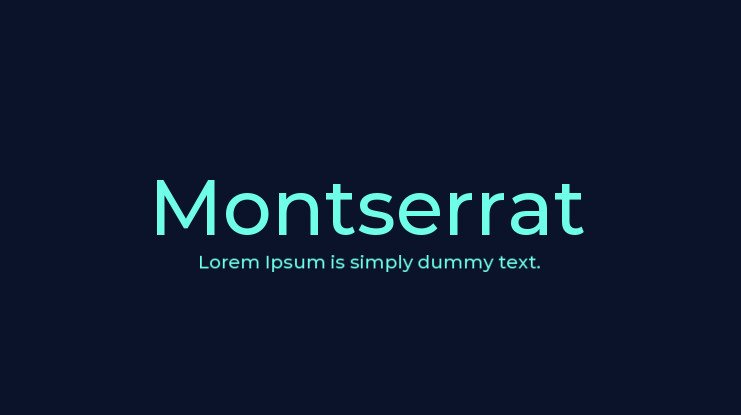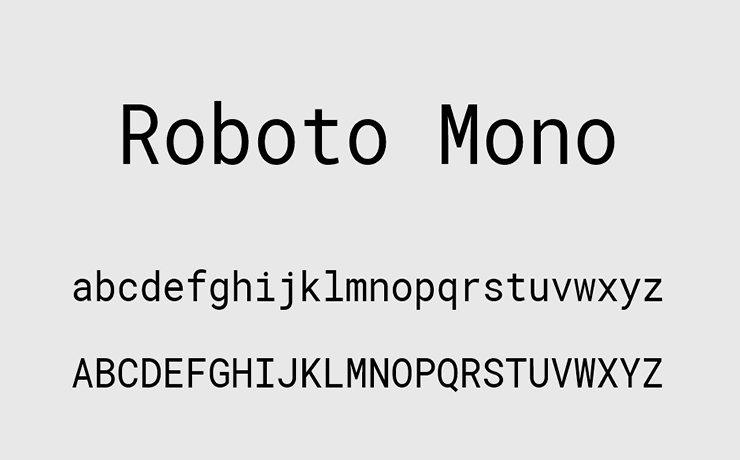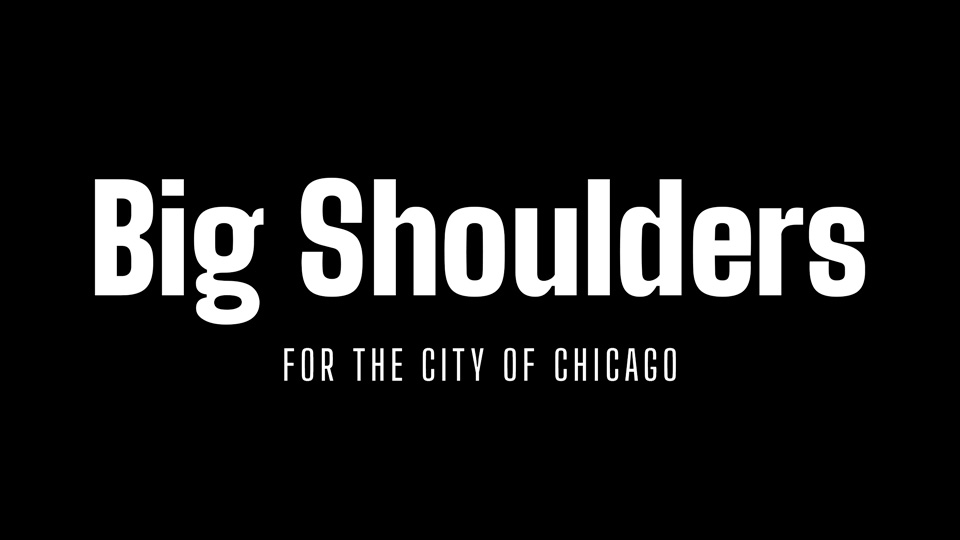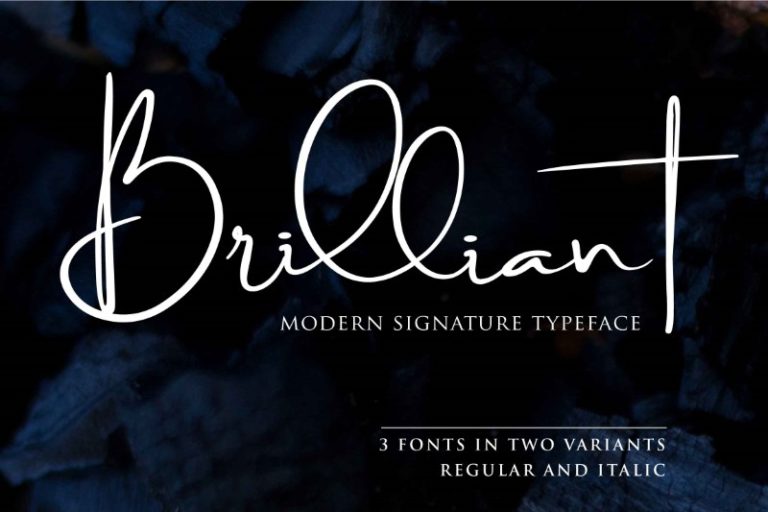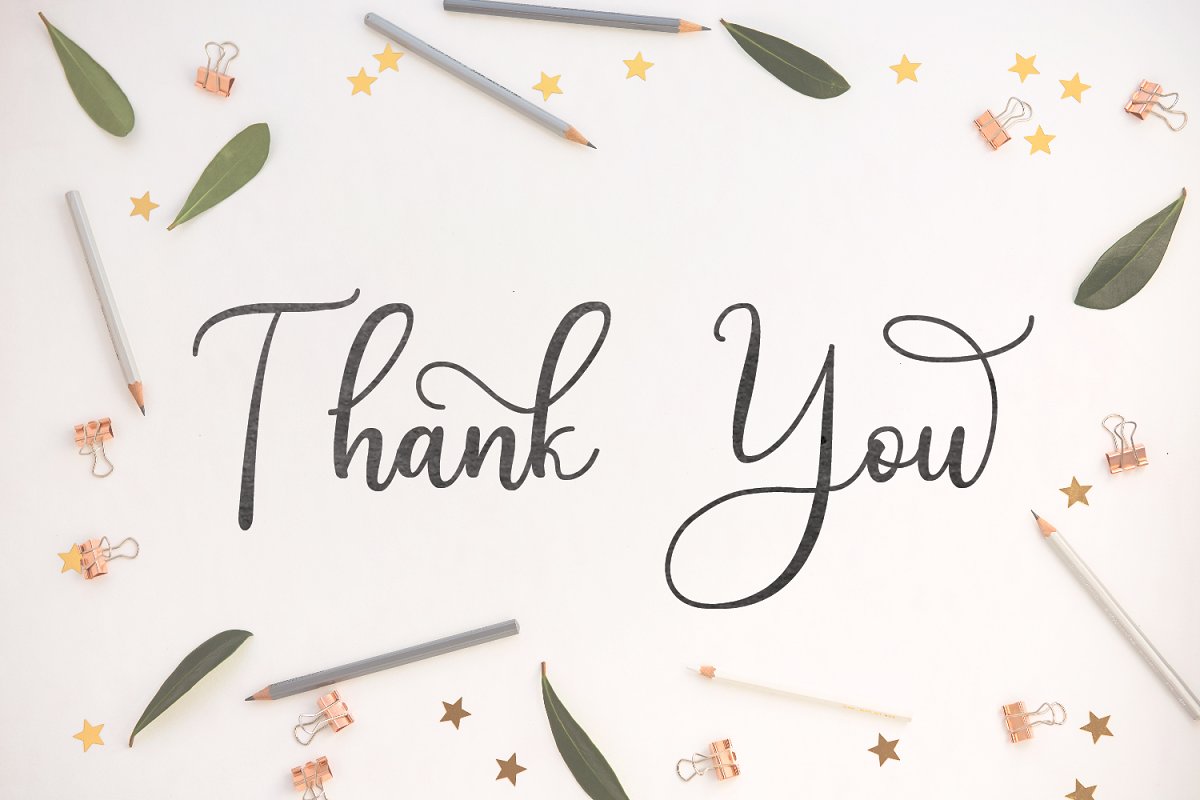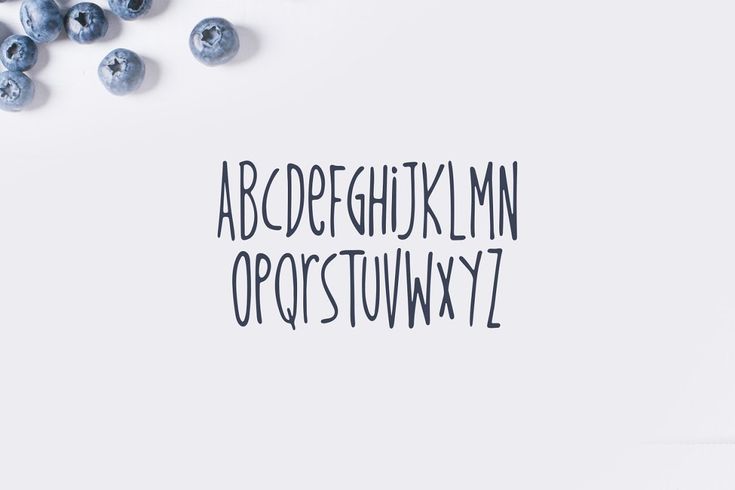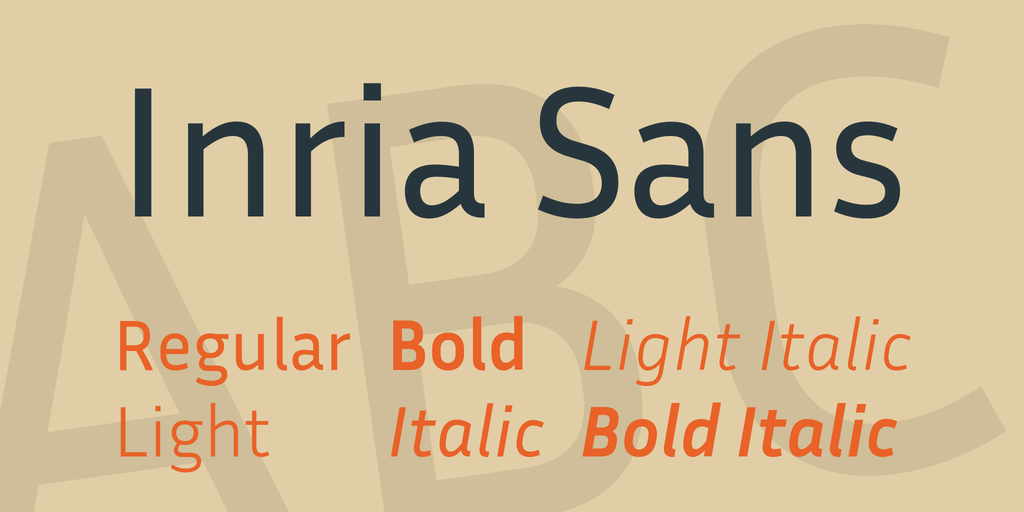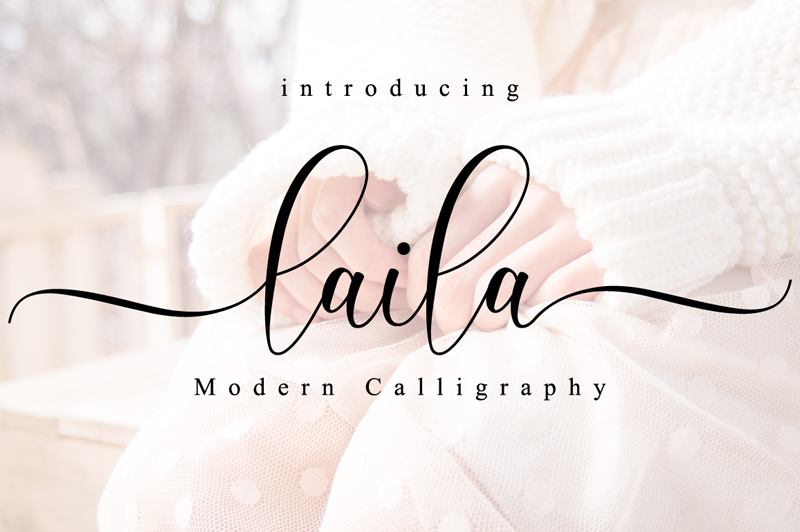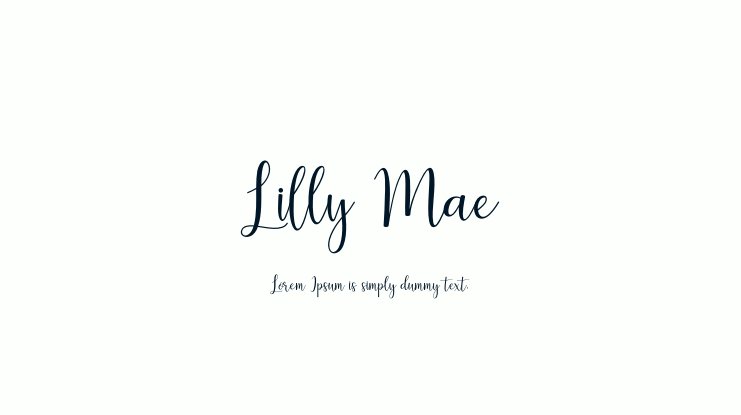
Để có một tác phẩm hoàn chỉnh, thu hút được người người xem, các designer thường sử dụng những font chữ đẹp cho thiết kế để giúp những tác phẩm trở nên sáng tạo, chuyên nghiệp hơn. Mỗi font chữ khác nhau đều biểu đạt những tính cách, thông điệp riêng biệt mà tác phẩm muốn hướng đến. Hãy cùng tìm hiểu những font chữ đẹp cho thiết kế đang được các designer ưa chuộng nhất hiện nay nhé!
Bộ sưu tập Font chữ thiết kế
Laila font
Font chữ này là kiểu kết hợp kết cấu tự nhiên với độ cứng của serif, rất thích hợp để dùng cho việc tạo thêm các điểm nhấn trên homemade vào thiết kế bao bì hoặc in ấn cần cảm giác hữu cơ, nuôi trồng tại nhà.
Piazzolla font
Các designer muốn có một máy đánh chữ cổ cho thiết kế, sự phá cách hơn thông qua các nét chữ với độ đậm nhạt khác nhau, các mẫu chữ không đồng nhất mà một chiếc máy đánh chữ có thể tạo ra, thì font chữ Piazzolla chính là sự lựa chọn xứng đáng nhất. Sự pha trộn giữa các nét dày và mảnh chắc chắn sẽ tạo nên một bộ những glyph xuất sắc.
Inria Font
Font chữ này là sự kết hợp hoàn hảo giữa hai phong cách: một chút kiểu serif và loại có các nét cong đặc sắc. Sự kết hợp tuyệt vời này  tạo nên một văn bản với diện mạo kiểu cách và ấn tượng.
Almendra font
Font chữ serif này tạo cho người xem một cảm giác retro ngộ nghĩnh nhưng vẫn giữ được phong cách sành điệu. Với sự đa dạng glyph để chọn lựa, Almendra chắc chắn sẽ giúp cho những thiết kế của bạn mang một diện mạo ấn tượng và độc đáo.
Cormorant Upright font
Những thiết kế mang phong cách vintage thì Cormorant Upright chính là sự lựa chọn tuyệt vời nhất. Phong cách in tay xen kẽ và điểm thêm một số vectơ, font chữ này giúp tạo ra những thiết kế cổ điển rất phù hợp cho các logo và thiết kế in ấn.
Neuton font
Neuton là một kiểu font chữ thanh lịch, sang trọng cùng sự hỗ trợ đa ngôn ngữ. Neuton chắc chắn sẽ là font chữ hàng đầu trong bộ sưu tập của một nhà thiết kế ngôn ngữ.
Kurale font
Một serif thú vị khác không thể bỏ qua Kurale. Với các nét chữ hoa xen kẽ, mẫu chữ handmade được tạo ra một cách cẩn thận, font chữ này là một câu trả lời tuyệt vời để tổng hợp hình ảnh một máy in độc đáo cho nhiều loại thiết kế.
Italiana font
Một sự kết hợp của sự tinh tế và tao nhã với font chữ kiểu vẽ tay. Font chữ Italiana thường được sử dụng cho các nội dung blog, tài liệu marketing.
Im Fell English SC font
Im fell english sc là một font chữ có một sự thu hút đặc biệt đối với người xem. Font chữ cá tính, mang đậm tính nghệ thuật này là một sự bổ sung thú vị cho bất kì một designer nào để khiến những tác phẩm thiết kế trở nên hấp dẫn hơn, đặc sắc hơn.
Bangers font
Bangers loại font chữ tròn trịa, đáng yêu mà bất cứ nhà thiết kế nào cũng đều muốn có trong bộ sưu tập của mình. Cho dù dự án của bạn là để cho in ấn hay trang web, font chữ này sẽ vẽ lại nội dung một cách dễ dàng, dễ dọc theo cách tinh tế.
Montserrat font
Những tấm áp phích và biển hiệu cũ trong khu phố Montserrat truyền thống của Buenos Aires đã truyền cảm hứng cho Julieta Ulanovsky thiết kế kiểu chữ này và giải cứu vẻ đẹp của kiểu chữ đô thị nổi lên vào nửa đầu thế kỷ XX.
Sansita Swashed font
Một phiên bản trang trí công phu của Sansita, với các chữ cái viết hoa cong, một số chữ cái viết thường thay thế nhất định và các chữ ghép mới.
Sansita Swashed được thiết kế bởi Pablo Cosgaya (Omnibus-Type) và được phát triển bởi Aldo De Losa.
Roboto Mono font
Các phông chữ được tối ưu hóa để dễ đọc trên màn hình trên nhiều loại thiết bị đọc khác nhau.
Big Shoulders Stencil Display font
Bạn có thể sử dụng chúng một cách tự do trong các sản phẩm và dự án của mình – in ấn hoặc kỹ thuật số, thương mại,…
Comfortaa font
Comfortaa là một thiết kế kiểu sans-serif. Nó hoàn toàn miễn phí, cho cả mục đích sử dụng cá nhân và thương mại.
Nerko One font
Nó mang lại một cái nhìn sôi nổi, thú vị và hiện đại.
Phông chữ viết tay Việt hóa
Ariel Signature
Ariel là một trong những kiểu font chữ đẹp mang phong cách độc đáo, bắt chước lối viết tay thực tế tương đối tự nhiên, có các nét đứt nét và bản chất tối giản. Với kiểu font chữ này, thiết kế của bạn sẽ mang đặc sắc riêng, có thể sử dụng cho các sản phẩm đồ họa dùng trong truyền thông xã hội hoặc tạo ra một mẫu logo có một không hai.
Stantic Typerface
Đây là kiểu chữ có thể gây ấn tượng đến khán giả của bạn. Một phong cách mới mẻ với những chữ cái dài và độ dày đường nét mạnh mẽ, font chữ này rất phù hợp cho thiết kế liên quan đến văn phòng phẩm, biển hiệu ngoài trời hoặc các loại tài liệu thương hiệu.
Casterio Signature
Thư pháp từ xưa đến nay vẫn luôn là một trong những kiểu chữ được ưa chuộng với các đường nét uốn lượn đẹp đẽ và mềm mại. Với sự phát triển của công nghệ thì Casterio Signature chính là một sự kế thừa thú vị của kiểu chữ thư pháp. Đây là kiểu chữ script liền mạch mang phong cách viết tay tuyệt đẹp, tưởng như được vẽ bằng tay trên tác phẩm. Font chữ đẹp này thường được sử dụng trong thiết kế tài liệu về đám cưới, tạp chí và các sản phẩm.
Apple Juice Font
Dân designer chuyên nghiệp có thể đã biết đến một số phông chữ sans-serif có kiểu dáng cứng nhắc, nhưng Apple Juice chính là một sự khác biệt. Font chữ Apple Juice có vẻ ngoài mang đường nét vui tươi, thú vị, khá phù hợp cho các ấn phẩm dành cho trẻ em.
Love Rosnita Font Duo
Đây là một sự kết hợp khá đẹp mắt với bộ đôi font chữ Love Rosnita. Mặt trước là phông chữ script đẹp mắt kết hợp với kiểu sans-serif ở phía sau tạo ra hiệu ứng thú vị cho những thiết kế poster của bạn.
Pixie Ring Font
Có lẽ bạn đã biết, một trong nhiều lợi ích của các gói phông chữ là phần tặng thêm vô cùng thú vị và Pixie Ring là một trong số đó. Đây là một trong những kiểu font chữ đẹp được tạo ra bằng các chữ cái dễ thương, quyến rũ, cùng với các chi tiết kèm theo như hình trái tim hay kim cương, giúp thiết kế của bạn bắt mắt và thu hút hơn nhiều.
The Slowbird Typeface
Slowbird chính là một trong những font chữ đẹp cho thiết kế với các chi tiết script thanh lịch, nét chữ ngọt ngào. Kiểu chữ này phù hợp với những bức hình minh họa đáng yêu cho bìa sách dành cho trẻ em hoặc chiếc thiệp mời nho nhỏ mang phong cách của riêng bạn.
Lúna Font Family
Lúna chính là một trong những font chữ đẹp vừa đơn giản, lại vừa sang trọng, phù hợp với chủ đề gia đình. Không chỉ có một số loại tập tin chất lượng cao mà gói phông chữ này còn bao gồm các ký tự đa ngôn ngữ để hỗ trợ thiết kế bổ sung nếu muốn.
Bware Typeface
Bware là một kiểu phông chữ viết tay đích thực và có cả một gói nghệ thuật vector miễn phí cho bạn thỏa sức sáng tạo. Để có được gói phông chữ này, bạn cần trả phí ban đầu, và sau đó bạn sẽ nhận được ngay quyền truy cập vào hàng loạt hình dạng và vector vô cùng thú vị. Đây chính là phông chữ tạo nên nét riêng biệt trong chiếc logo của chính bạn.
Periwinkle Typeface
Đây là phông chữ mang nét thủ công, đáng yêu với những nét chữ được kéo dài, có thể áp dụng cho cả chữ hoa và chữ thường tạo ra sự kết hợp hết sức thú vị. Ngoài ra, gói cũng được bao gồm các ký tự thay thế mang đến cho bạn nhiều lựa chọn hơn.
Little Summer Font
Little Summer mang đến cho thiết kế của bạn một chút mùa hè đầy thú vị. Kiểu font chữ này phù hợp với các dự án hoạt hình hoặc sách dành cho trẻ em với phong cách đơn giản, nhẹ nhàng pha chút đáng yêu. Ngoài ra, gói cũng bao gồm các ký tự Latin cơ bản kèm theo các con số và ký hiệu.
Sweet Belly Font
Một cái tên ngọt ngào cũng sẽ mang đến những thiết kế ngọt ngào. Chính Sweet Belly với kiểu chữ script và sans-serif cùng các vector bổ sung mang đến cho bạn một chiếc  thiếp mời hay tờ rơi ngọt ngào, gần gũi.
Brilliant – 3 Signature Font
Gói ba font chữ chữ ký Brilliant sẽ mang đến một phong cách cá nhân cho riêng bạn với những đường nét phóng khoáng, đầy sức thu hút. Kiểu này rất thích hợp trong thiết kế logo, văn phòng phẩm và nhiều ấn phẩm khác nữa.
Quartz Script
Với dạng chữ vô cùng đơn giản, đậm nét, bắt chước chữ viết tay thực tế hoặc vẽ doodle mang lại cảm giác gần gũi là điểm đặc sắc của font chữ Quartz. Hãy dùng Quartz thêm một chút phong cách cho các tác phẩm của chính bạn.
Lemonade Script Font
Lemonade Script sẽ mang đến cho bạn một ly nước ép làm dịu cơn khát mùa hè ngay trong chính thiết kế của bạn. Đây là kiểu thủ công, phong cách với nhiều ký tự thay thế sống động. Font chữ này phù hợp để bạn tạo ra những tác phẩm typography tuyệt vời kèm theo các từ ngữ hay câu trích dẫn yêu thích của bạn.
Lavanda Typeface
Đây là một font chữ đẹp cho thiết kế, được sử dụng nhiều trong các dự án sáng tạo, bạn có thể dùng nó trong thiết kế các hình ảnh thú vị đăng blog hay tạo ra một chiếc logo độc đáo.
West Side Font
West Side mang phong cách cổ điển nhưng lại có các chi tiết tuyệt đẹp và góc cạnh. Để tạo nên được một thiết kế đẹp mắt, thú vị, bạn nên kết hợp font chữ này với các động vật dễ thương.
Debby Font
Với chữ viết script móc và có kết cấu thô ráp, giống giấy, chính là font chữ đẹp được sử dụng khá nhiều trong các thiết kế thiệp chúc mừng, thiệp mời đám cưới hoặc logo, đó là Debby.
Lilly Mae Font
Lilly Mae là kiểu font chữ đẹp mang nét hiện đại nhưng lại xoắn vòng đầy tinh tế, thích hợp dùng trong các thiết kế thủ công hoặc kỹ thuật số.